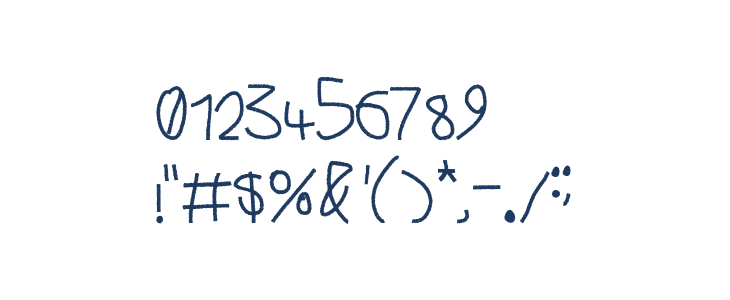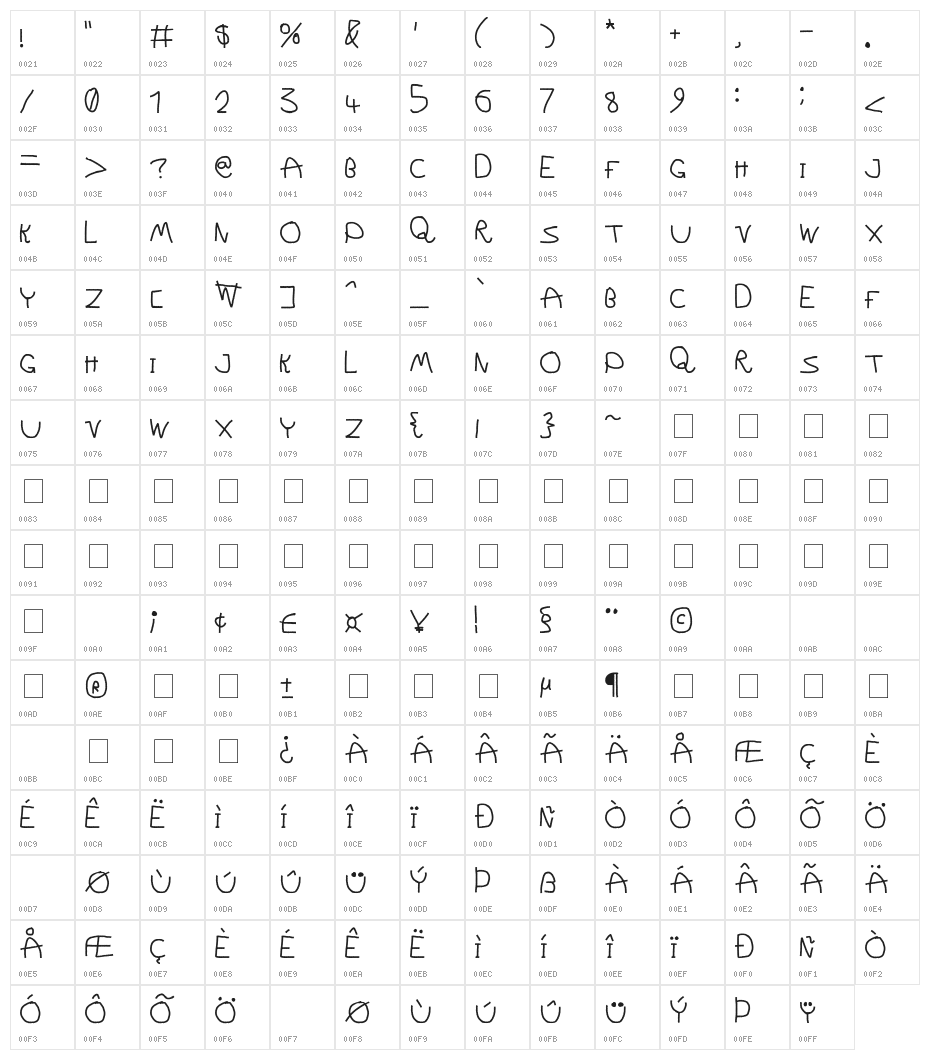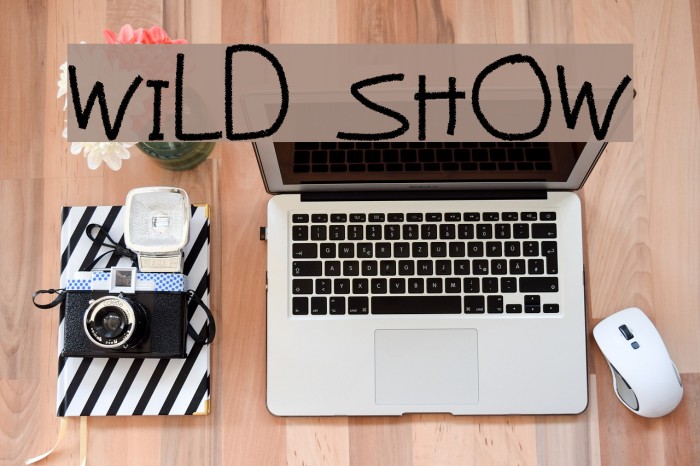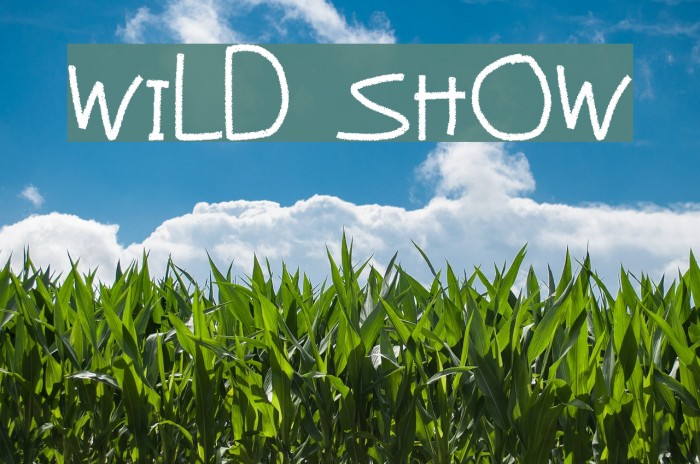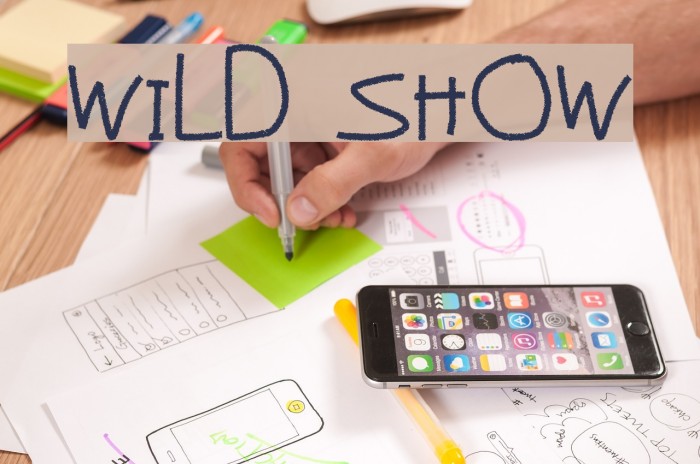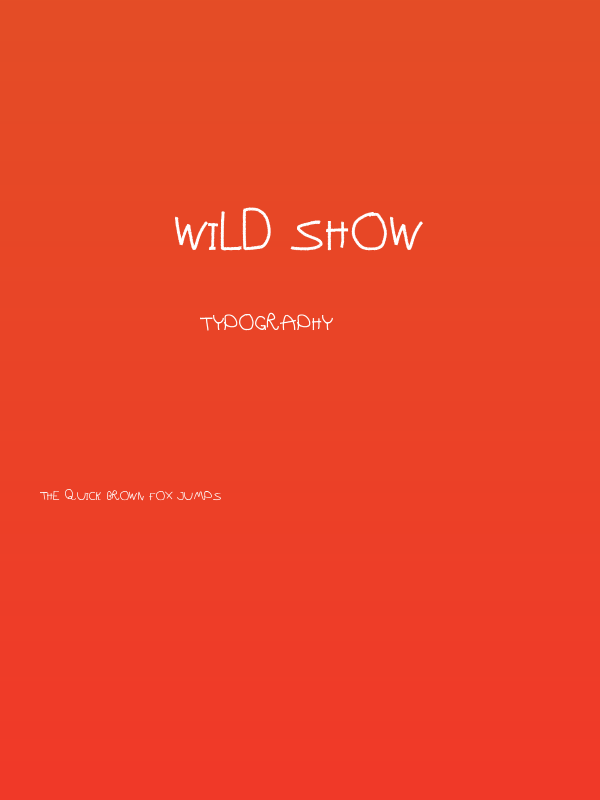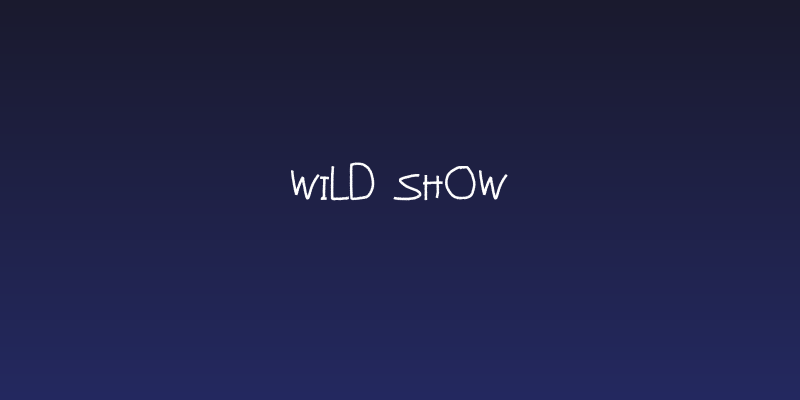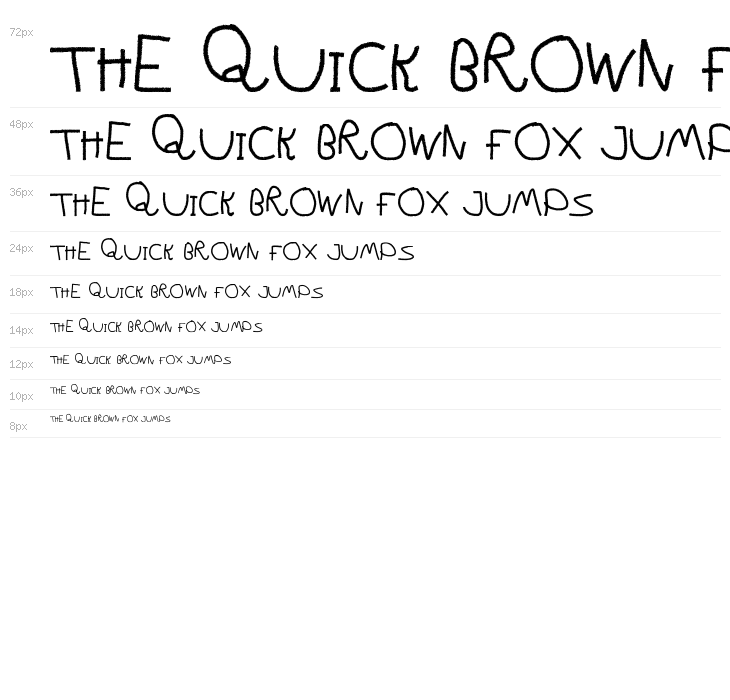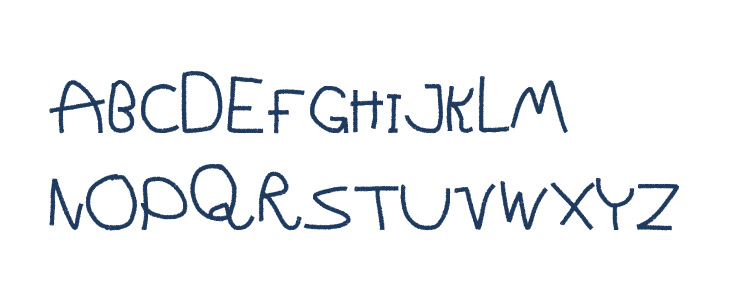
Wild Show Font
| Stile generale | Casual |
| Caso d'uso | Headlines, Informal text, Personal projects |
| Progetti proposti | Ideal for greeting cards, children's books, casual invitations, and personal branding. |